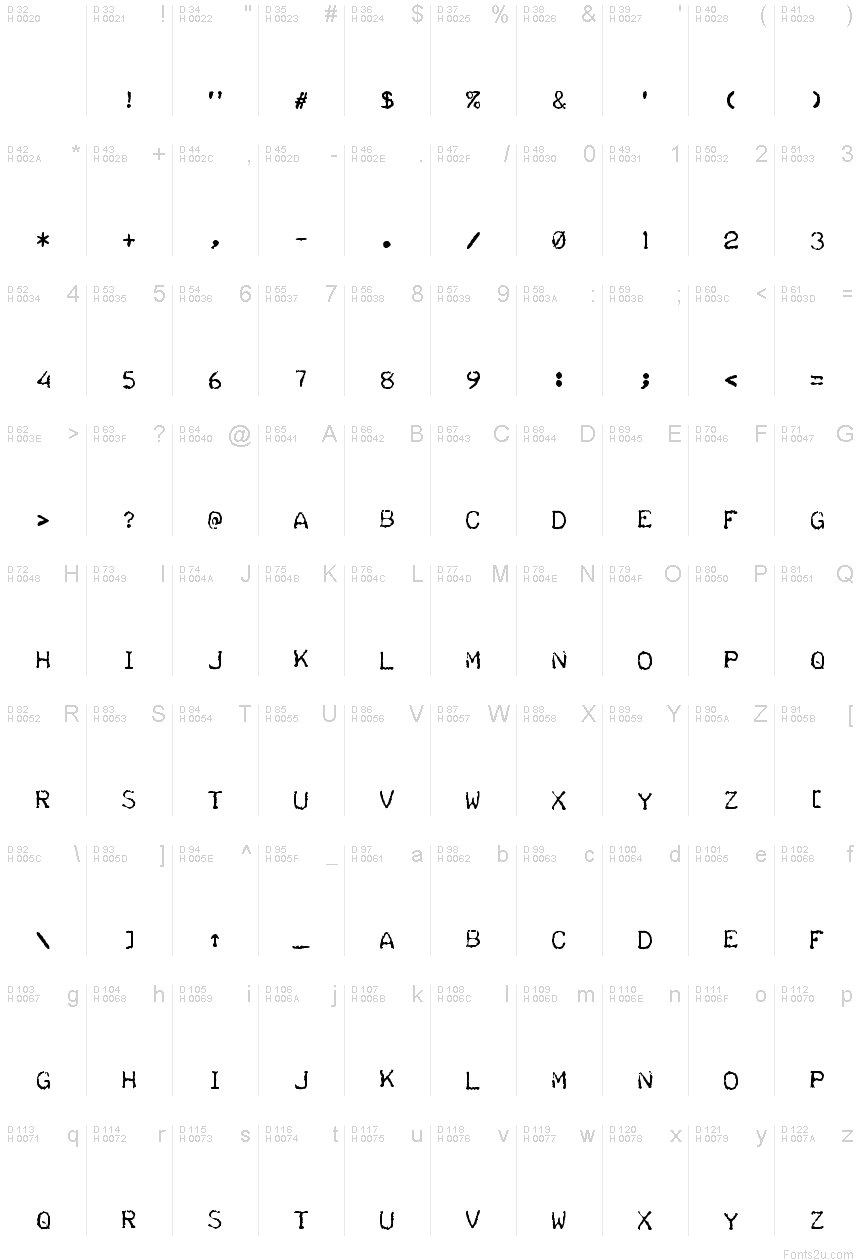
Teleprinter Intalic, darmowy, postarzany font typu display autorstwa Marka Zanziga, bazuje na klimacie starej drukarni z szorstkimi szeryfami i krawędziami, które sprawiają wrażenie rozpływających się. Litery wyglądają na zużyte, poplamione i nieco nieokiełznane, jakby odbito je na kiepskim papierze ze zbyt dużą ilością farby, co nadaje krojowi surowy, maszynowy charakter zamiast sterylnego, cyfrowego wykończenia.
Świetnie sprawdza się w nagłówkach plakatów, okładkach książek w stylu pulp, tytułach zinów, kartach tytułowych oraz na opakowaniach, gdzie pożądana jest tekstura nadruku, a nie kliniczna precyzja. Jako darmowy font, doskonale nadaje się również do krótkiego brandingu, grafik eventowych i wszędzie tam, gdzie te poszarpane kontury mają przyciągać wzrok.